「文字の母たち Le Voyage Typographique」のおしらせ
港千尋「文字の母たち Le Voyage Typographique」
インスクリプトより、写真家・評論家の港千尋さんの最新写真集「文字の母たち Le Voyage Typographique
」が刊行されました。
「文字の母たち Le Voyage Typographique」と見本帖・パターン・原字・電胎母型
世界でもっとも古い印刷所のひとつ、パリ・フランス国立印刷所、秀英体活字を伝える東京・大日本印刷――。いまや絶えようとする活版金属活字の最後の姿をとらえ、文字の伝播の歴史を繙く最新写真集。
ガラモン体に始まるアルファベットをはじめ、楔形文字やヒエログリフ、ギリシア、アラビア、エチオピア、ヘブライ、ジャワ、チベット、そして漢字と仮名……、2006年に閉鎖されたパリ・フランス国立印刷所は、グーテンベルク以降の西欧の活版印刷技術を伝承し、近代から現代に至る活字書体の発展にも大きな影響を与えてきました。また東京・大日本印刷は日本における明朝体金属活字の精華・秀英体を伝えてきました。本書は、パリと東京で撮影を重ね、活字に凝縮された東西文明の交流と最後の職人たちの姿を見事に写しだした類のないフィールドワークです。
ひょんなご縁で、港さんにDNP市谷工場の活版印刷現場をご覧頂く機会が生まれました。
和文活版の現場はDNPにとってはあたりまえのものでしたが、フランス国立印刷所に通って撮影を行った港さんには、むしろ新鮮にうつったようです。
特に文選の部屋では、活字サイズごとに壁のように並ぶ活字棚(ウマ)を目にした途端、「あ、違う!」とひとこと。欧文の場合一般的に活字ケースを植字台にセットし、文選しながら文字を組んでいます。しかし和文組版には膨大な量の漢字があるため、利用頻度・部首などでいくつかに分類し、見えるように棚に配置し、文選にも専門の職人が配置されます。
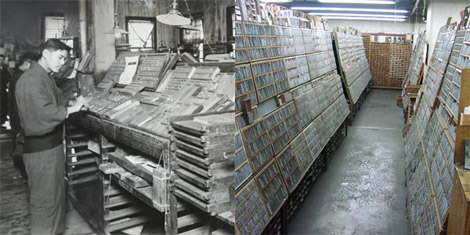
古いですが大正11年の欧文植字のようすと現在の和文の活字棚。欧文ではこういう活字棚はないそうです。
フランス国立印刷所にももちろん明朝体活字が保管されていますが、日常的に用いるものではありませあんので、普段は引き出しの中。フランスの職人さんは、「漢字ってあんなにたくさんどうやってしまっているの?」と疑問だったそうです。そう言われればそうですね。
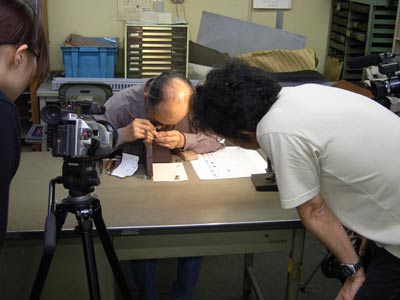
直彫り職人の中川原さんの撮影中。港さんもじいっとその技術に見入っています。
文選職人の山口さんの撮影中。実はウン年ぶりに文選をしたとのこと。
大日本印刷の前身である秀英舎は、明治9年に、まだ日本に入ってきて間もない金属活版印刷会社として誕生しました。中国で生まれた漢字が、大陸の西の端のフランスで明朝体活字となり、宣教師たちの手で中国に帰って来ます。そして上海から長崎の本木昌造のもとへ、明朝体活字と活版技術が渡り、次第に日本国内に産業としての金属活版印刷が伝播していきます。本木の高弟・平野富二が興した東京築地活版製造所(平野活版)から活字を導入していた秀英舎は、やがて自社で活字の開発を始めます。その自社書体は、東京築地活版製造所の「築地体」と並び、後世の和文書体に大きな影響を与えるまでに完成度を高め、「秀英体」と呼ばれるようになりました……。